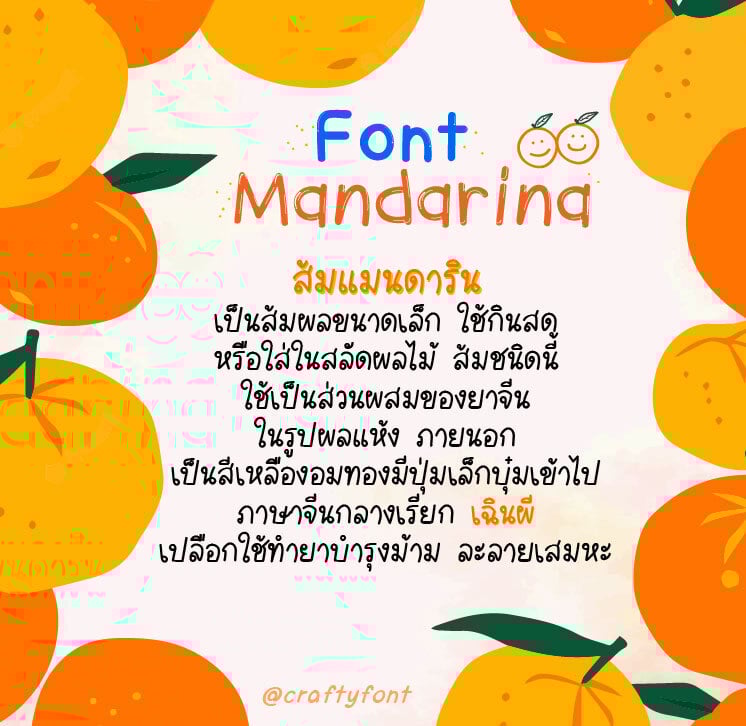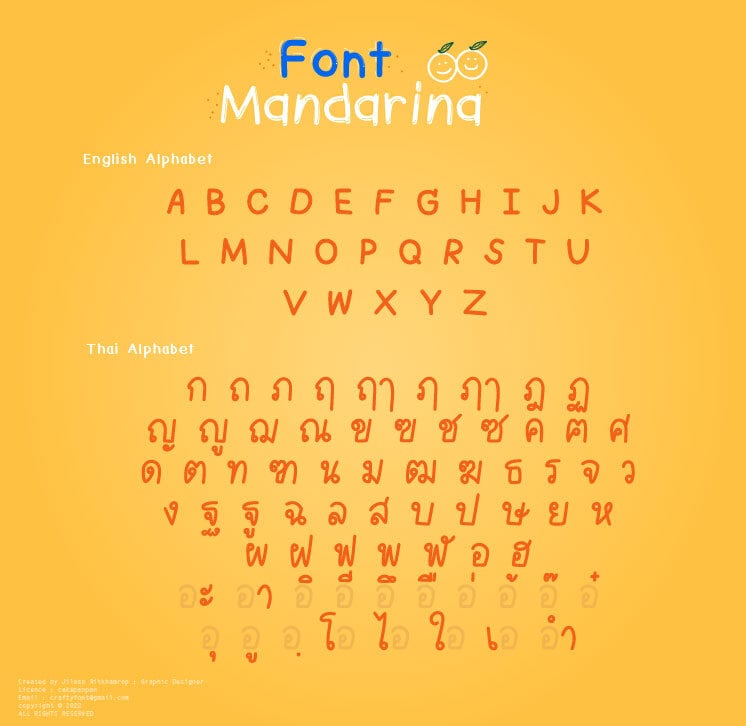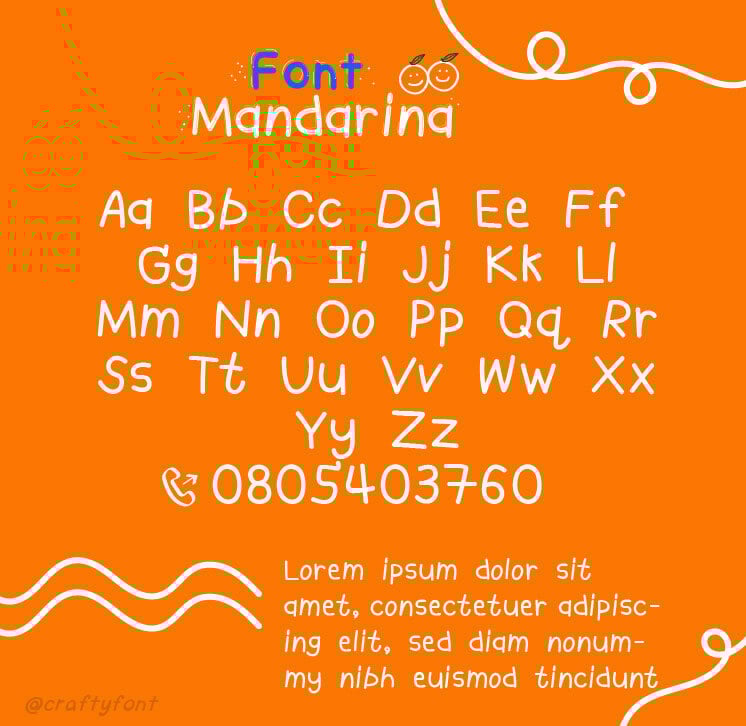
Mandarina Font (ฟอนต์แมนดาริน)
ฟอนต์เลม่อน ซนๆ เปรี้ยวปรี๊ด วิตามินซีสูง หวังว่าทุกคนจะชอบนะคะ 🧡🍊🍊
ฟอนต์แมนดาริน มีทั้งภาษาไทยและภาษาอังกฤษ แฟมิลี่เซ็ตนี้มี 6 ขนาดด้วยกัน ทั้งตัวหนา ตัวปกติ ตัวบาง และตัวเอนสำหรับทุกน้ำหนัก สัญลักษณ์บวกลบคูณหารมีให้ใช้ครบ ฝากไว้ในอ้อมอกอ้อมใจพี่จ๋าด้วยนะจ๊ะ 🥰